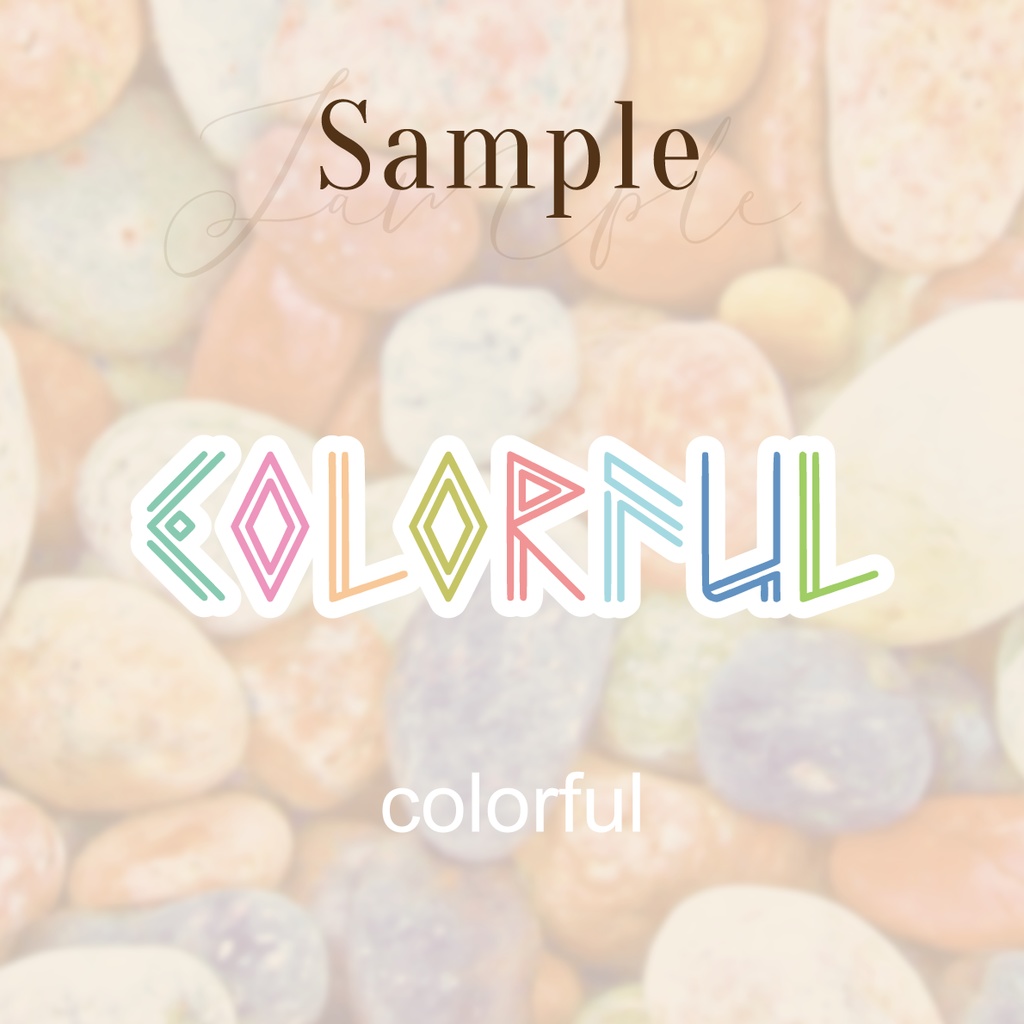
ルーニックフォント
「古代文字を意識したなんかオシャレなフォント」をテーマに作られました。タイトルロゴやデザインの一部として使いやすい...気がします。カーニング必須。 【収録文字】 ◇Read Me(txt.) ◇フォント(otf. / ttf.) 英語アルファベット(大文字・小文字) ※基本、大文字も小文字も同じ形 【注意事項】 ◇いろいろ“甘い”です。お遊び程度にご利用ください。 ◇商用・非商用を問わず無料でご利用いただけるフリーフォントですが、著作権は放棄していません。 ◇無保証です。自己責任でご利用ください。 ◇予告なしにフォントデータを編集・改良などする可能性があります。 【禁止事項】 ◇フォントデータの改変・無断転載・再配布・販売(フォントそのものの改変などは禁止していません。ex.) Adobe Illustratorなどのソフトでフォントをアウトライン化し、編集する) ◇このフォントを利用した制作物(ロゴなど)の商標登録 ◇公序良俗に反する利用 常識の範囲内での利用をお願いしています。